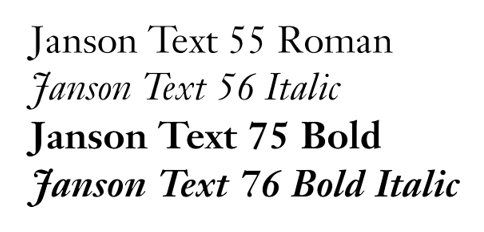
Nummern in Schriftbezeichnung
Ich hätte eine allgemeine Frage:
Was bedeuten die Nummern in manchen Schriftbezeichnungen? Beispielsweise "Frutiger 57 CN", "Frutiger 47 LightCN", "Helvetica 96"...
Hat das irgendwas mit der Dicke zu tun? Das wäre das einzige, was ich mir selbst zusammenreimen könnte... das ist aber wahrscheinlich ein Blödsinn!
Das Ziffernsystem wurde von Frutiger eingeführt, um eine logische und einfache (eingängige) Systematik der Stilbezeichnungen zu ermöglichen. Die erste Ziffer steht für die Strichstärke (Gewicht), die zweite für die Breite (Weite) des Schriftschnittes; wobei gerade Ziffern anzeigen, dass es sich um einen kursiven (obliquen) Schnitt handelt. Die 55 stellt immer den Mittelwert dar (Regular).
So bedeutet 45 als, dass es sich um einen Light-Schnitt der Regular handelt; die 46 wäre der gleiche in Kursiv; die 43 die Extended-Version und die 47 die Condensed der Light. Eigentlich ganz einfach und logisch...
Später wurde die Doppelzahl durch eine Tipple-Zahl ersetzt, um die Strichstärken-Systematik noch feiner zu modulieren.
Dieses System wurde auch bei der Frutiger, der Helvetica und der Rotis verwendet, hat sich aber leider nie richtig durchsetzen können.
leider verstehe ich das system (sofern ein logisch nachvollziehbares system dahinter ist) deinen ausführungen zufolge nicht ganz. kennt dazu jemand eine genauere beschreibung, konnte nichts dazu finden.
auf der seite 100besteschriften fand ich dazu eigentlich auch keinen artikel...
noch einmal ausführlich: bei beiden schriften gibt die erste ziffer die strichstärke an.
frutiger
4 = light · 5 = roman · 6 = bold · 7 = black · 8 = extrablack · 9 = ultrablack
helvetica
2 = ultra light · 3 = thin · 4 = light · 5 = roman · 6 = medium · 7 = bold · 8 = heavy · 9 = black · 10 = extra black
bis hierhin finde ich das system nachvollziehbar. die zweite ziffer benennt nun eine weitere eigenschaft:
frutiger
5 = regular · 6 = italic · 7 = condensed
helvetica
3 = extended · 5 = regular · 6 = oblique · 7 = condensed
das heißt, du kannst jetzt – soweit die entsprechenden schnitte existieren – nummern kombinieren. die frutiger 46 ist die frutiger light italic, die frutiger 87 ist die frutiger extrablack condensed. die helvetica 33 ist die helvetica thin extended, die helvetica 77 ist die helvetica bold condensed. die klassifikation versagt allerdings, wenn – sagen wir mal – die helvetica extended oblique, die es tatsächlich gibt, damit beschrieben werden soll, da kursiv und extended über dieselbe ziffernposition bezeichnet werden. man müsste also regular/kursiv alleine auf die zweite ebene stellen und für die schriftweite eine dritte ziffer anhängen. da diese systeme ohnehin nicht mehr sonderlich verbreitet sind, wird das vermutlich kein mensch mehr weiterentwickeln, sondern auf die nummerierung verzichten oder dieses »problem« eben akzeptieren.
eine neuere schrift, die ein vergleichbares system verwendet, allerdings nur mit einer ziffer, ist die thesis basic von luc(as) de groot:
Dieses System wurde auch bei der Frutiger, der Helvetica und der Rotis verwendet, hat sich aber leider nie richtig durchsetzen können.
mir faellt spontan nur noch die knockout von hoefler ein.
hat jemand noch andere beispiele auf tasche?
mir faellt spontan nur noch die knockout von hoefler ein.
hat jemand noch andere beispiele auf tasche?
Die Knockout von Hoefler hat wiederum ein völlig eigenes Ziffernsystem, welches mit dem hier genannten nicht vergleichbar ist.
das war mir schon klar ... mir ging es eher um weitere schriften
die auf ein zahlensystem zu benennung der schnitte zurueckgreifen.